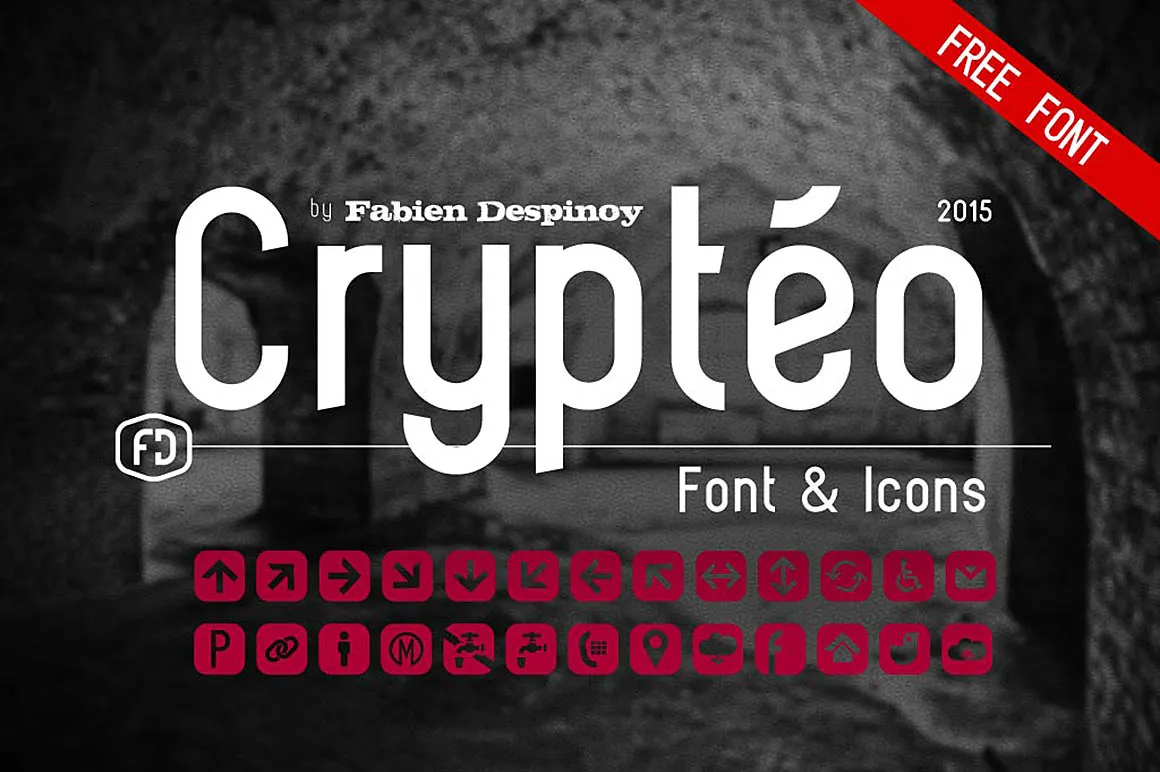
Crypteo Font – Download Grátis
A fonte ‘Crypteo Font’ é uma elegante fonte sans serif criada por Hamilton. Esta opção customizada está disponível gratuitamente e apresenta uma aparência arredondada e moderna, que combina bem com textos decorativos e desenhados a mão. Uma das características mais chamativas desta fonte é o seu estilo elegante, adequado para uso em projetos gráficos de design personalizado ou até mesmo na criação de logos sofisticados. Como uma opção da categoria de fonts decorativas, ela se destaca pela sua capacidade de criar um toque único e diferenciado em qualquer projeto que use. Recomendamos a fonte ‘Crypteo Font’ para aqueles procurando por uma fonte customizada e moderna para dar um toque especial às suas criações gráficas.